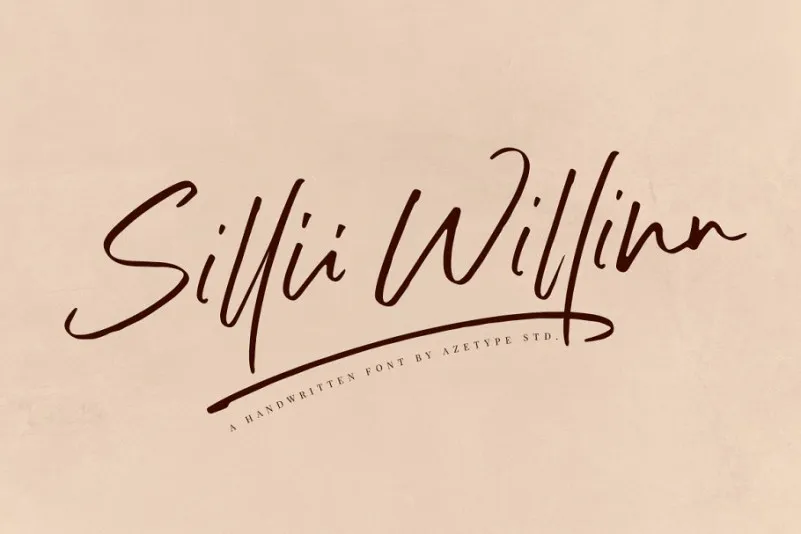
Sillii Willinn Handwritten Font – Fonte Grátis
Sillii Willinn Handwritten Font
A Sillii Willinn Handwritten é uma fonte escrita à mão com um belo ar contemporâneo, criada para adicionar um toque moderno a seus projetos de design. Esta fonte elegante e sofisticada faz par perfeito com diversos tipos de trabalhos gráficos que exigem um touch pessoal. Seja para anúncios de casamento, criação pessoal, logotipos ou embalagens de produto, esta fonte escrita à mão captura a essência da sua ideia de forma única e criativa. Sillii Willinn é uma fonte versátil que traz uma verdadeira marca à cada letra, dando aos projetistas a liberdade de explorar diferentes estilos sem comprometer seu estilo único. Não esperemos mais – deixem Sillii Willinn Handwritten dar sua assinatura ao seu próximo projeto visual.